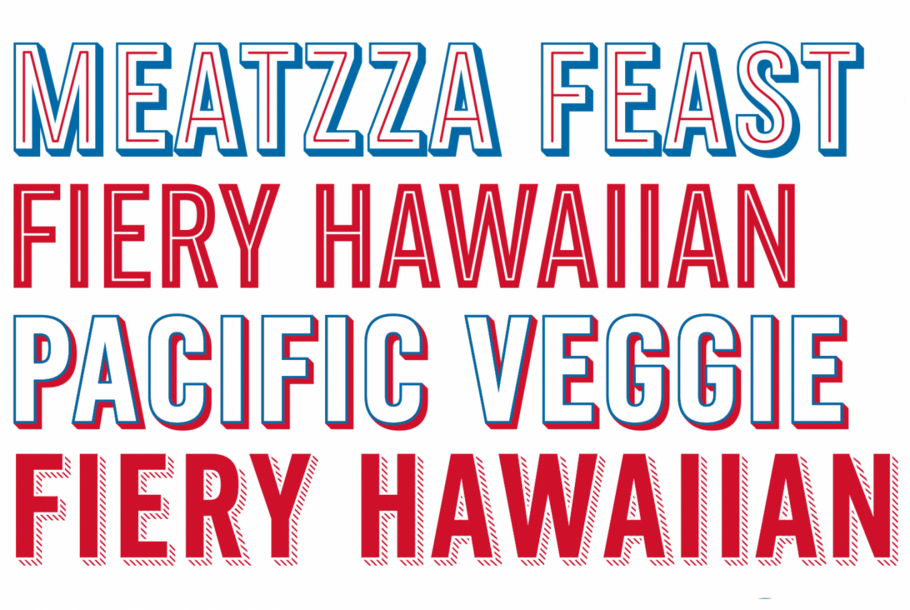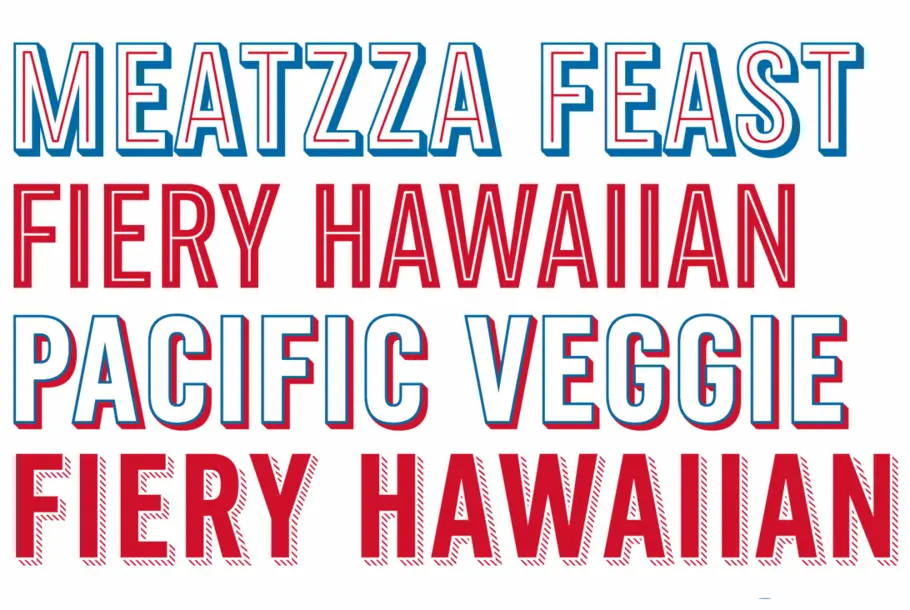
Domino’s Pizza(ドミノ・ピザ)のための、組み合わせ自由自在なモジュール式マルチレイヤーフォントを開発
MonotypeのデザイナーTerrance Weinzierlは、モジュール式のマルチレイヤーフォントであるPizza Press書体で、ドミノ・ピザにモダンなアメリカーナテイストを届けました。
この書体はドミノ・ピザを担当していたアメリカの広告代理店Crispin Porter + Bogusky社の要請に応えて作成されました。
書体デザイナーのWeinzierlは、すでに使用されていたTrade Gothic®と一緒に使用した際に、コンテンポラリーな印象を作り出すことができる書体の作成を依頼されました。Weinzierlは、既存のロゴやデザインを分解してフォントにそれらを反映しさまざまなパターンで組み合わせることができる一連のモジュールフォントを作成することで、これまでベクター化や細かい調整を必要としていたタイポグラフィの作成にかかる負荷を軽減させ、デザイナー、さらには一般の人にもこのフォントを利用できるようにしました。
新しく開発されたPizza Press書体は、既存のTrade Gothic®書体のルーツである19世紀のオリジナルモデルに基づいて開発されています。開発するにあたって、Weinzierlは細かいディテールが施された金属活字時代の試料を研究し、細密な線状のストライプが過去にどのように作られたかを研究しました。Gill Sans® Shadowフォントも技術面で参考にしています。
「シャドウのデザインには、各文字への微細な調整が必要でした」
この新書体は、シャドウのウェイトの各文字の中でのストライプの角度と間隔が、手作業で調整されています。その他、字形がインラインウェイトを保持できるようにGから突起を取り除くといった細かい配慮もなされています。
また、このデザインでは、スクリーンで表示すると背景色が透けるように、アウトラインウェイトとシャドウのウェイトとがわずかに重なる部分へ組み込みのインキトラップを施しています。Weinzierlは、幅広いサイズと印刷環境で機能するように、レギュラーやディスプレイといった、アンティークなストライプウェイトに視覚的な微調整を行ったバリエーションも作成しました。
「 「非常に時間と労力を必要としていたプロセス、つまり、アウトライン化されたベクターアートを手作業でレイアウトにコピー&ペーストする作業が、文字通りキーボードで入力するだけのごく簡単な作業に変わったのです!」 」
Crispin Porter + Bogusky社がMonotypeとのコラボレーションに踏み切ったのは、非常に高いレベルでの理解とディテールへのこだわりでした。同社のデジタルアセットマネージャー、Jake Harvey氏は次のように語っています。
「CP+Bでは、書体デザインにおける長年の経験を誇るMonotypeであれば、この『繊細さ』を十二分に理解し、最終製品でもオリジナルデザインの特徴と精神を活かしてくれるだろうという確信がありました」
また、この書体はデザイナーの制作時間の短縮も実現しました。Harveyの言葉を借りると、
「非常に時間と労力を必要としていたプロセス、つまり、アウトライン化されたベクターアートを手作業でレイアウトにコピー&ペーストする作業が、文字通りキーボードで入力するだけのごく簡単な作業に変わったのです」
この書体は、すでにパッケージ、看板、テレビコマーシャルで使用されており、今後もドミノ・ピザブランドのあらゆる環境で利用されていく予定です。また、Pizza Pressは、2014年にTDCの書体デザインエクセレンス認証のを受賞しました。